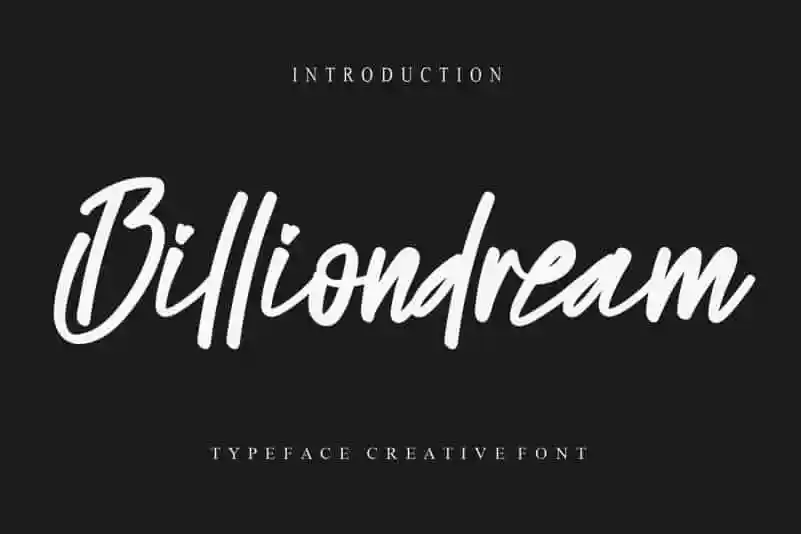
Billiondream Script Font – Download Grátis
Esta fonte chamada Billiondream Script Font é perfeita para quem busca uma mão-d escrita especial que vai dar vida a seus projetos digitais. Desenvolvida por creativeletter, esta elegante e fluida fonte de escrita à mão livre oferece um toque único que adicionará uma dose extra de originalidade aos seus trabalhos. A Billiondream Script Font é ideal para criar designs com alegria e vitalidade, seja em layouts pessoais ou profissionais. Suas linhas fluidas e seu estilo artesanal evocam sentimentos de criatividade e expressão única. Seja você designer gráfico, web designer, ou um fotógrafo que busca um visual atraente para seus trabalhos, esta fonte tem tudo o que você precisa. O seu design é perfeitamente adaptado para categorias como descrições em blogs, cartões de aniversário personalizados e editoriais de moda. A Billiondream Script Font não só adicionará profundidade aos textos, mas também fará com que eles chamem a atenção dos seus leitores. Seja você criando conteúdo digital ou estampando uma camiseta de skate, esta fonte é um recurso indispensável para designers gráficos em todo o Brasil e além.